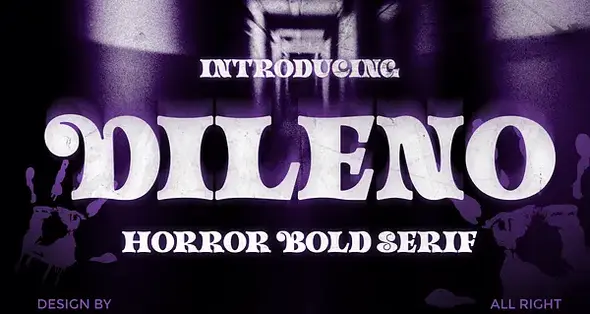
Dileno یک تایپفیس سریف جسورانه است که با الهام از زیباییشناسیِ ژانر وحشت طراحی شده است. این فونت با خطوط ضخیم، منحنیهای دراماتیک و بافتهای آسیبدیده، فضایی وهمآلود و در عین حال استایلیش خلق میکند که برای تمهای تاریک، مرموز و دلهرهآور بینظیر است.
حضور قدرتمند و بصری این فونت، آن را به انتخابی ایدهآل برای تایتل گرافی فیلمهای ترسناک، پوسترهای هالووین، برندینگ سبک گوتیک، جلد کتابهای جنایی و هر طرحی که نیاز به یک لمسِ جسورانه و شکارچیگونه دارد، تبدیل کرده است. ترکیب منحصربهفرد ساختار کلاسیک سریف با المانهای وحشت، به Dileno ظاهری متمایز و چشمگیر بخشیده که در هر پروژهای میدرخشد.
ویژگیهای کلیدی:
استایل قدرتمند و تاثیرگذار: مناسب برای جلب توجه آنی مخاطب
تم ترسناک و گوتیک: طراحی شده برای انتقال حس تعلیق و رمز و راز
بافتهای خاص: دارای جزئیات فرسوده که حس کلاسیک و قدیمی را تقویت میکند
موارد استفاده پیشنهادی:
تایتلبندی و عنوانبندی ویدیوهای سینمایی
پوسترهای فیلم و رویدادهای ژانر وحشت
طراحی جلد کتاب و مجلات فانتزی تاریک
لوگوهای خاص با هویت بصری گوتیک
تبلیغات و گرافیکهای شبکههای اجتماعی با تم هالووین